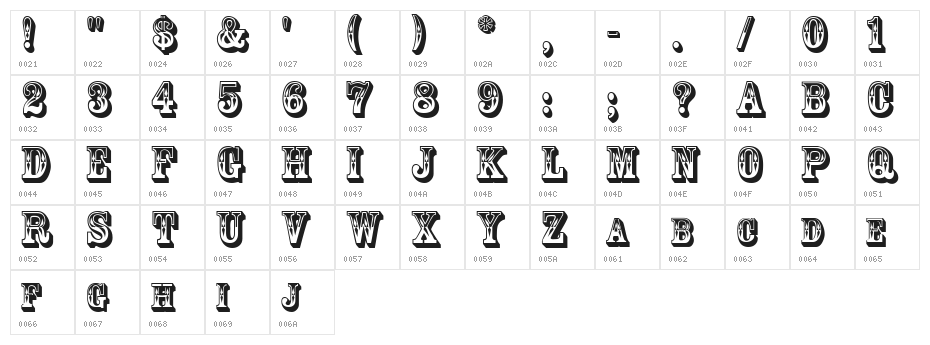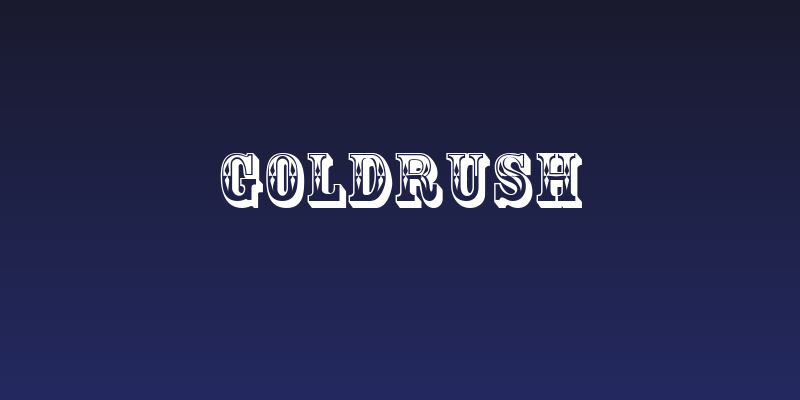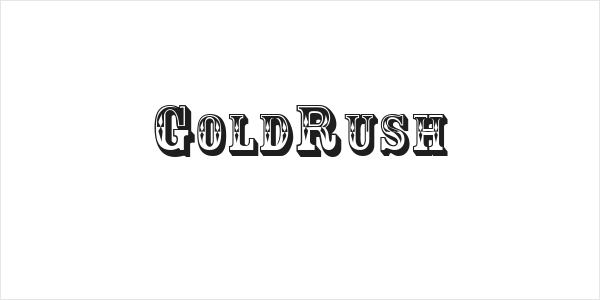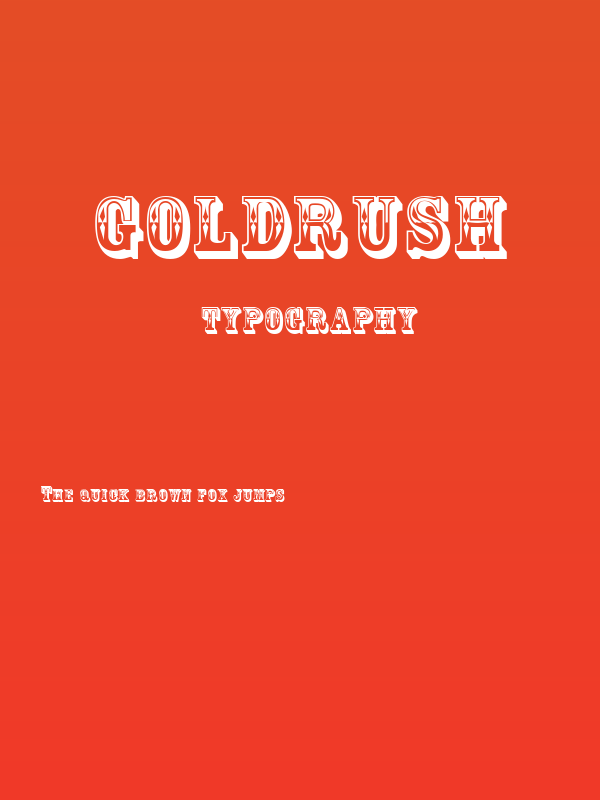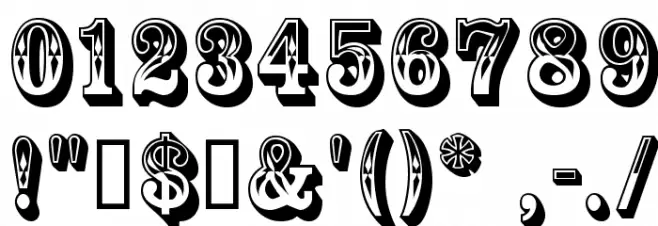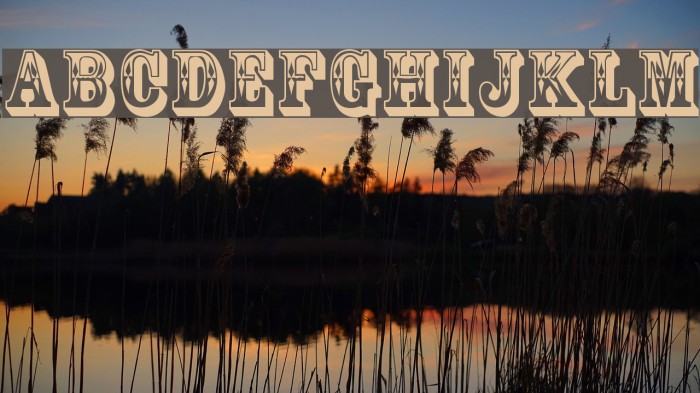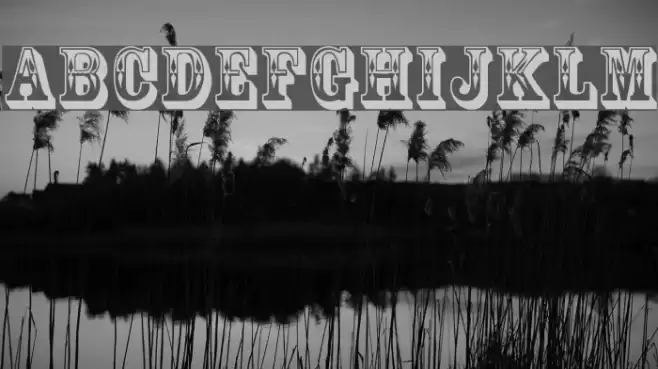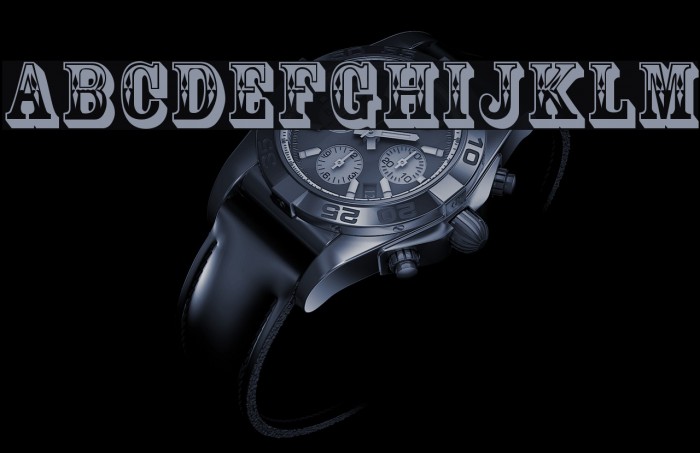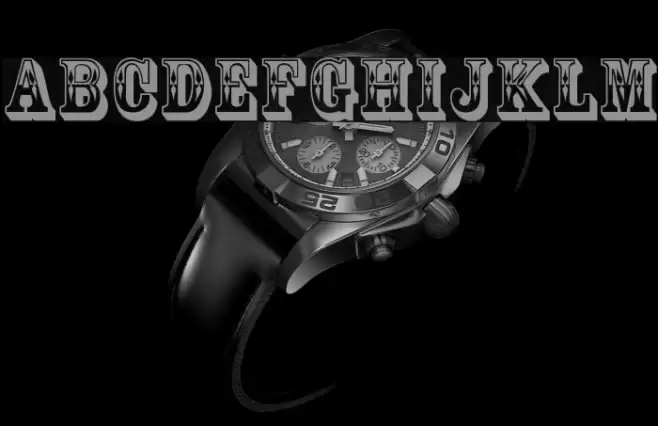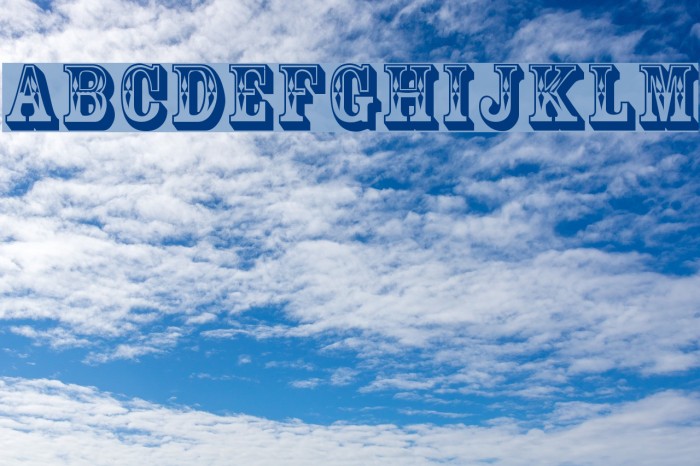
GoldRush Font
| Proiecte propuse | Ideal for use in vintage-themed posters, event invitations, branding for rustic or Western-style businesses, and decorative signage. |